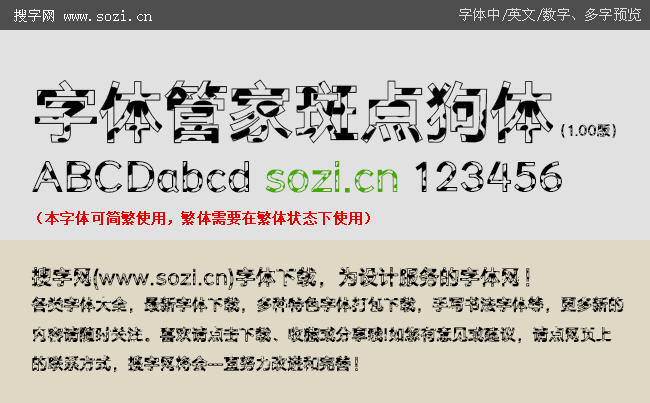
字體管家斑點(diǎn)狗體
搜字網(wǎng)給大家提供一款字體管家斑點(diǎn)狗體中文字體下載。字體管家斑點(diǎn)狗體以黑體字為原形,在字體內(nèi)部填充了斑點(diǎn)圖案,增加了趣味性,卡通味很濃。可用于包裝設(shè)計(jì),海報(bào)設(shè)計(jì),卡通畫冊(cè)等廣告設(shè)計(jì)場(chǎng)合。